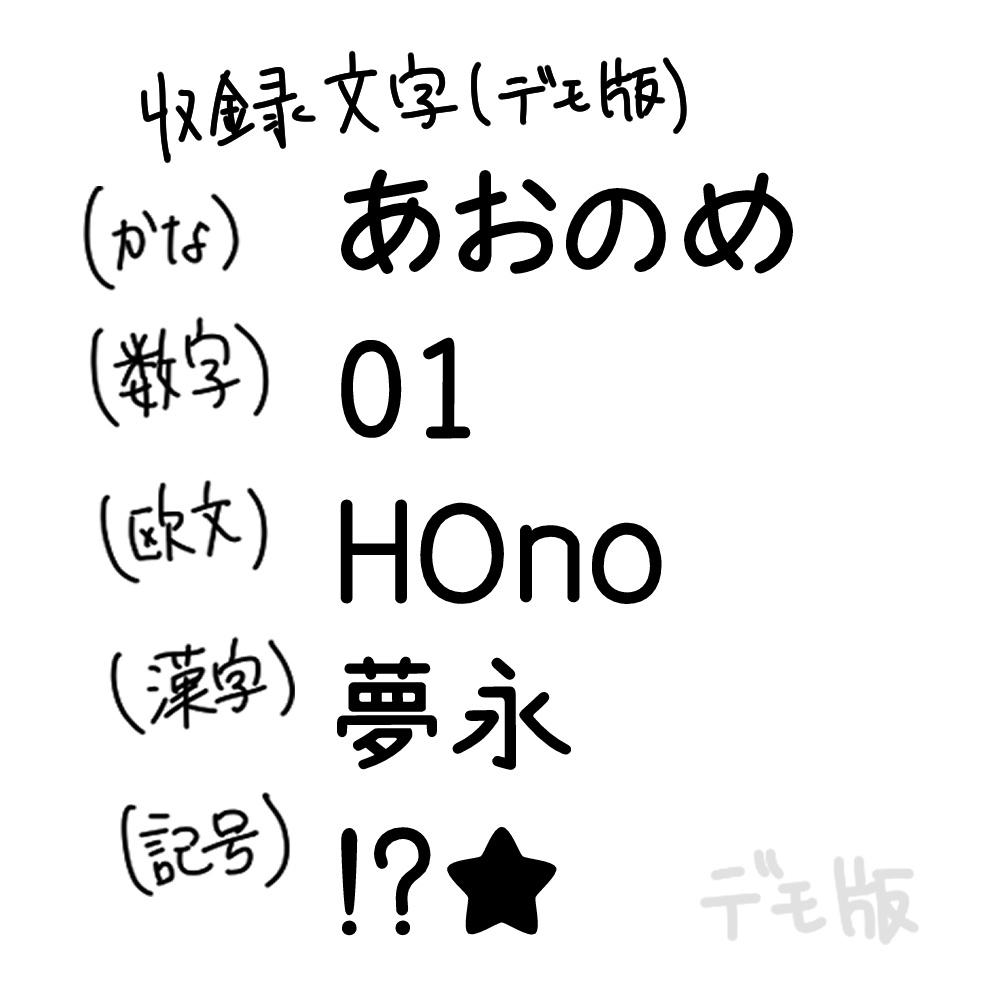
StellarCatsfont(星猫フォント)Demo版 v0.1
🌟 StellarCatsfont Demo v0.1(お試し版) 【このDemoは v0.1 で更新停止しています】 新しい文字や修正は 製品版 にのみ反映されます。 👉 製品版は今後BOOTHにて公開予定です。 --- ✨ 概要 | About StellarCatsfont(略称: SCF)の無料体験版です。 かわいさと読みやすさを両立した日本語フォントを、まずは雰囲気だけお試しください。 --- 📦 収録文字 / Included Glyphs かな: あ / お / の / め 欧文: H / O / n / o 漢字: 永 / 夢 数字: 0 / 1 記号: ! / ? / ★ 👉 ごく一部のサンプルのみ収録。実用には使えません。 --- 🚫 利用条件(Demo版) 非商用・非公開のプレビュー専用です。 公開コンテンツ(動画・配信・同人誌・印刷物・ロゴ等)への使用は禁止。 詳細は同梱の EULA.md をご確認ください。 --- ❓ FAQ(Demo版) Q. 商用利用できますか? A. できません。非商用・非公開のお試し専用です。 Q. 製品版はいつ出ますか? A. 2025年冬頃(予定)に v1.0 を公開予定です。進捗は FANBOX や作者のXで随時お知らせします。 --- 作者のX:さばかんⅡ(@SABAKAN_21_) https://x.com/SABAKAN_21_ FANBOX: https://sabakan2.fanbox.cc/ --- 🚀 製品版について - 商用利用OK - クレジット表記は任意(推奨) - 初期価格 500円 → 約300字ごとに +300円 → 最終 3,500円予定 - 購入者は1000字まで無料アップデート保証 👉 製品版は今後BOOTHにて公開予定です。 --- 📩 サポート Demo版は無保証・サポート対象外です。 技術サポート・不具合対応は製品版ご購入者さま限定となります。 --- ✅ Demo版は「まずは試してみたい」方向けの無料体験版です。 気に入ったらぜひ製品版で本格利用へ! 🎉 ※製品版は今後BOOTHにて公開予定です。 --- ※「応援DL(100円)」と「無料DL(0円)」で内容は同じZIPファイルです。 ご支援いただける方は応援DLをお選びください。制作の励みになります!🐾 --- 公開日 2025/08/30 更新日 2025/08/30 --- ©Stellar Cats Studio